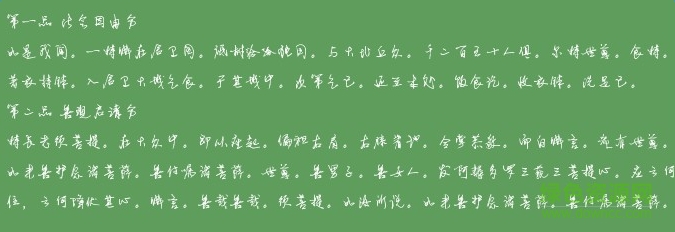
萬(wàn)有引力行書(shū)字體是葉根友字體中的一款行書(shū)字體,這款字體寫(xiě)出來(lái)的字是很好看的,字形行云流水,活潑自然,不像普通字體那樣呆板,喜歡這款字體的朋友可以來(lái)綠色資源網(wǎng)下載。
萬(wàn)有引力行書(shū)字體確實(shí)是很不錯(cuò)的一款電腦字體,實(shí)用性強(qiáng),可以用于很多方面,不管是書(shū)本印刷還是廣告設(shè)計(jì)等都是很合適的,歡迎大家來(lái)綠色資源網(wǎng)下載。